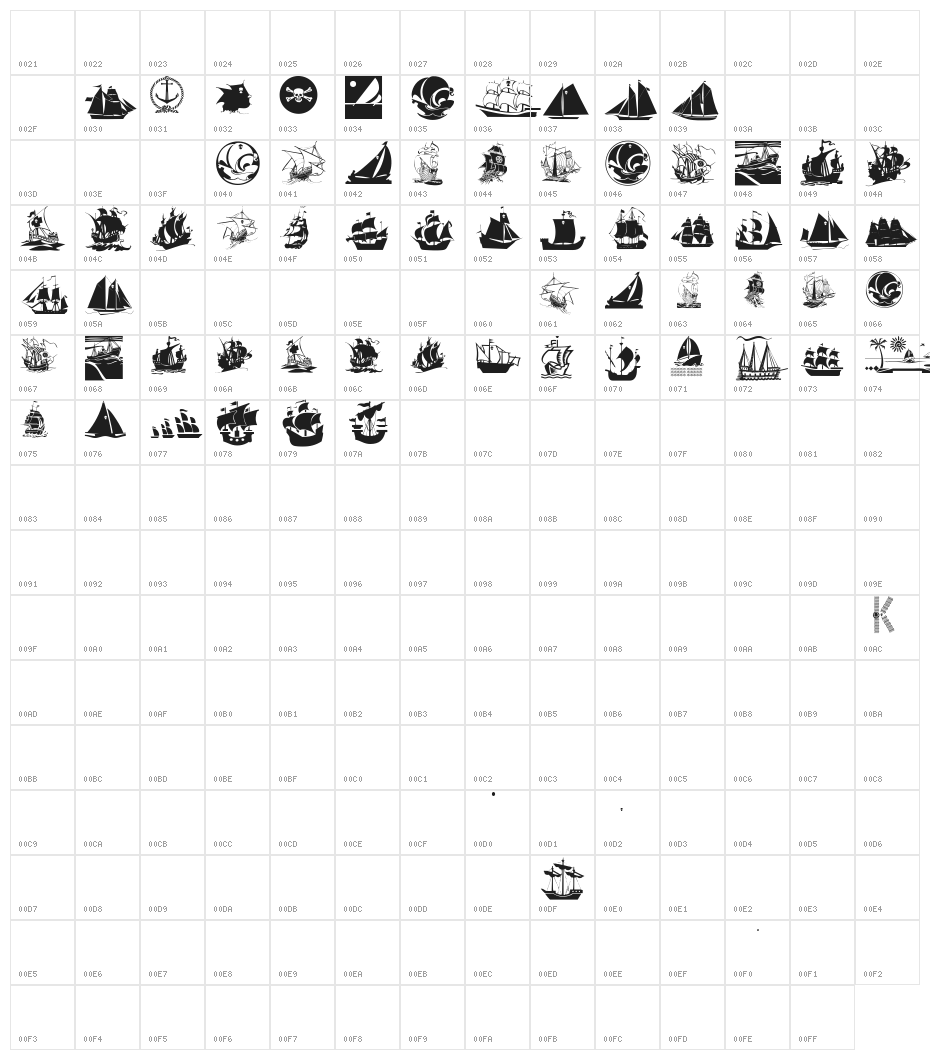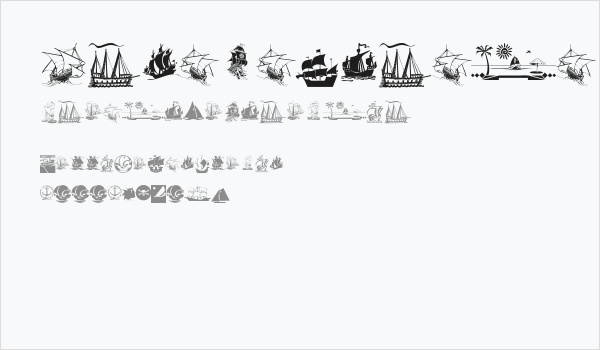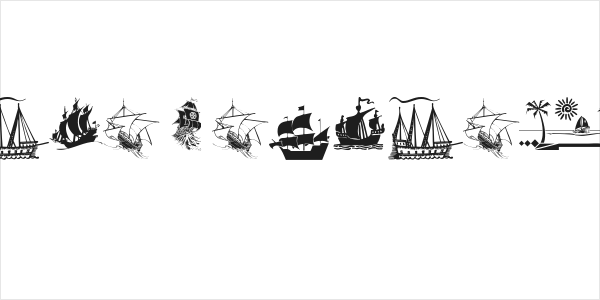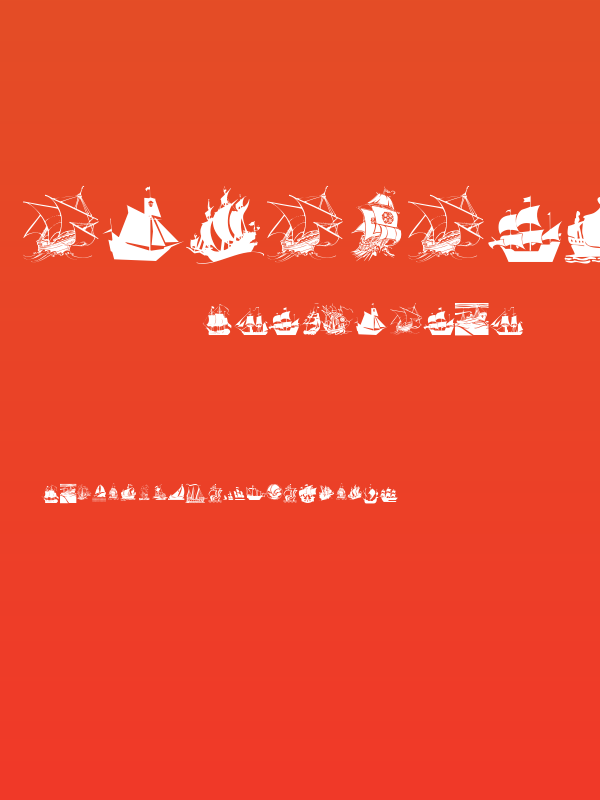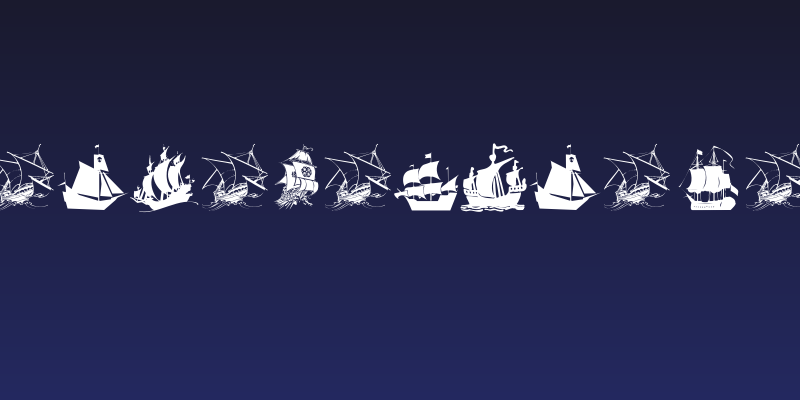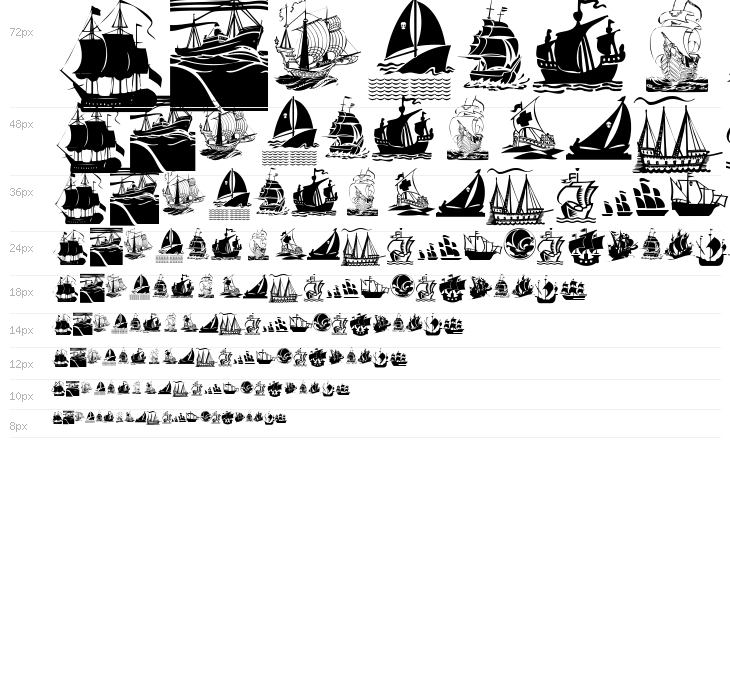
ArmadaPirata Font
✎ Dingbats
| Gesamtstil | Decorative, Thematic, Nautical |
| Anwendungsfall | Icons, Decorative elements, Themed graphics |
| Vorgeschlagene Projekte | Pirate party invitations, treasure maps, themed posters, children’s books, educational materials, event flyers, and branding for nautical or pirate-themed businesses. |